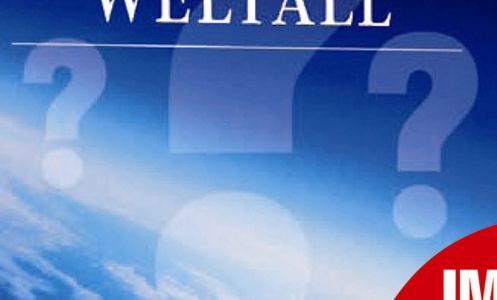
Ich suche dieses Fragezeichen:
Weiss jemand in welcher Schirftart das so vorkommt?
Keine genau gleiche, aber ähnliche:
Geometric 706 Black
Avenir LT 95 Black
Mach´ den Screenshot doch nochmal - und zwar mit dem roten Kreis. Wahrscheinlich ist das ja die gleiche Schriftenfamilien.
Nein, der rote Kreis wurde draufmontiert. Ist ein Preisschild...
Da die Fragezeichengruppe auf allen Covern der Reihe drauf ist, habe ich den Verdacht, dass sich da jemand was zusammengebastelt hat.